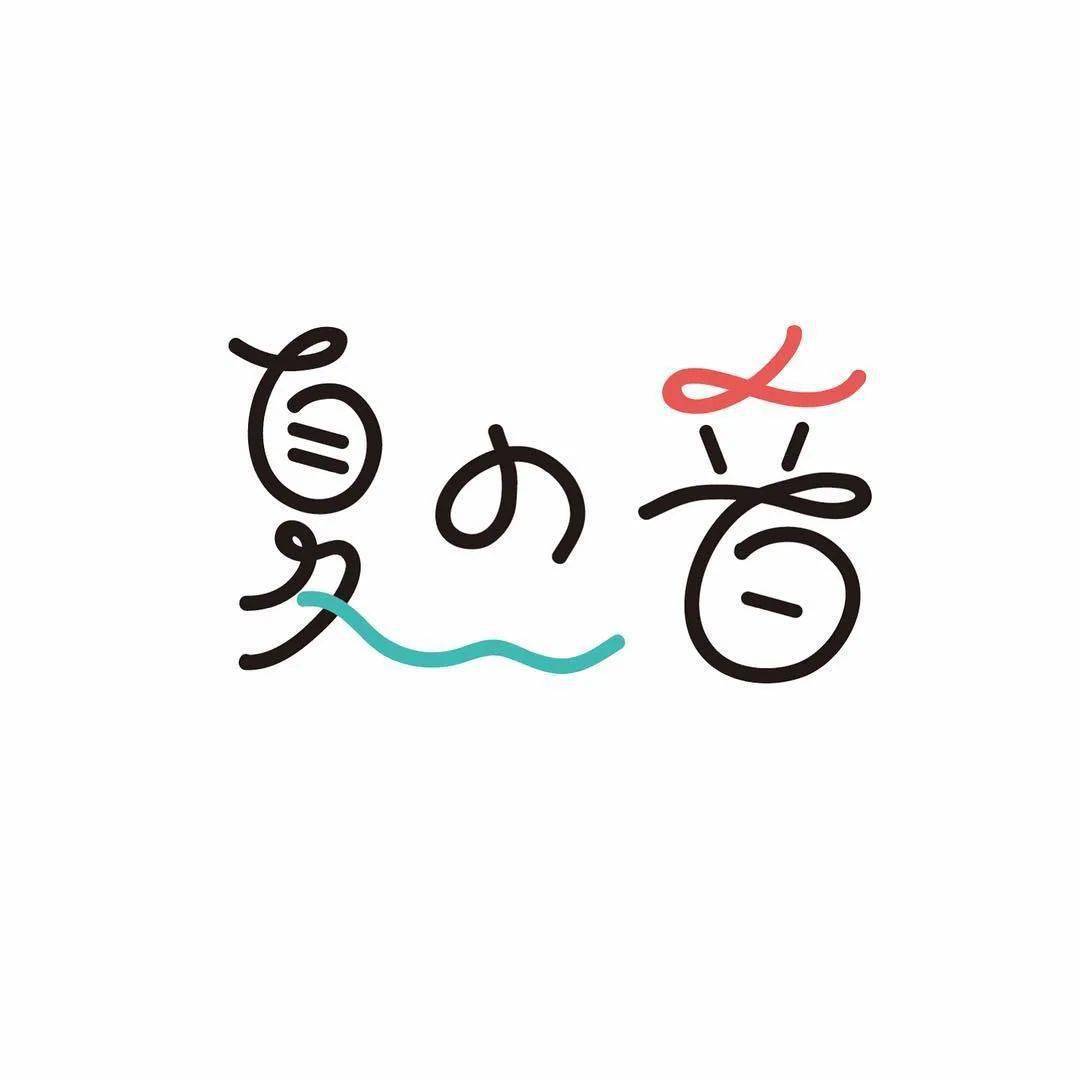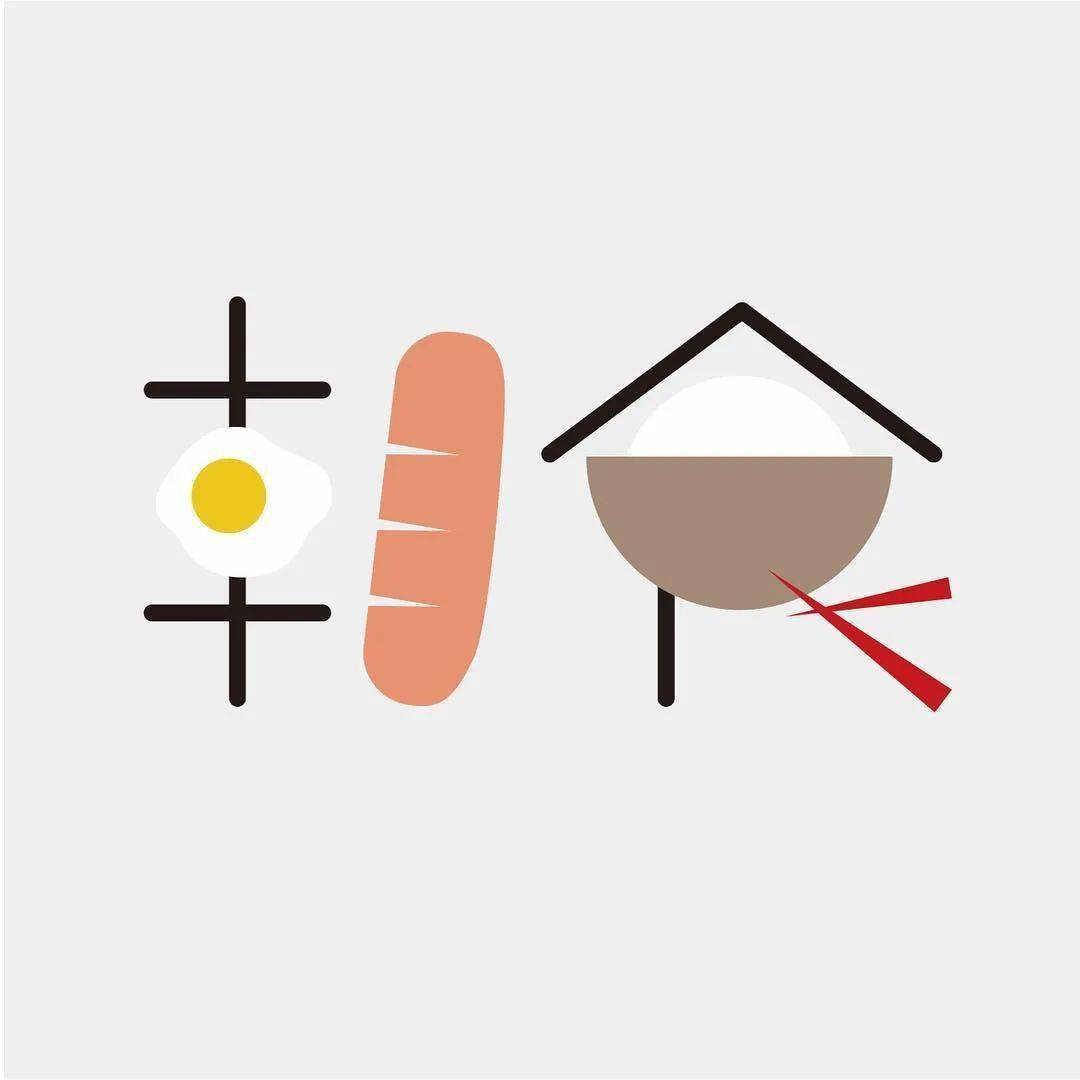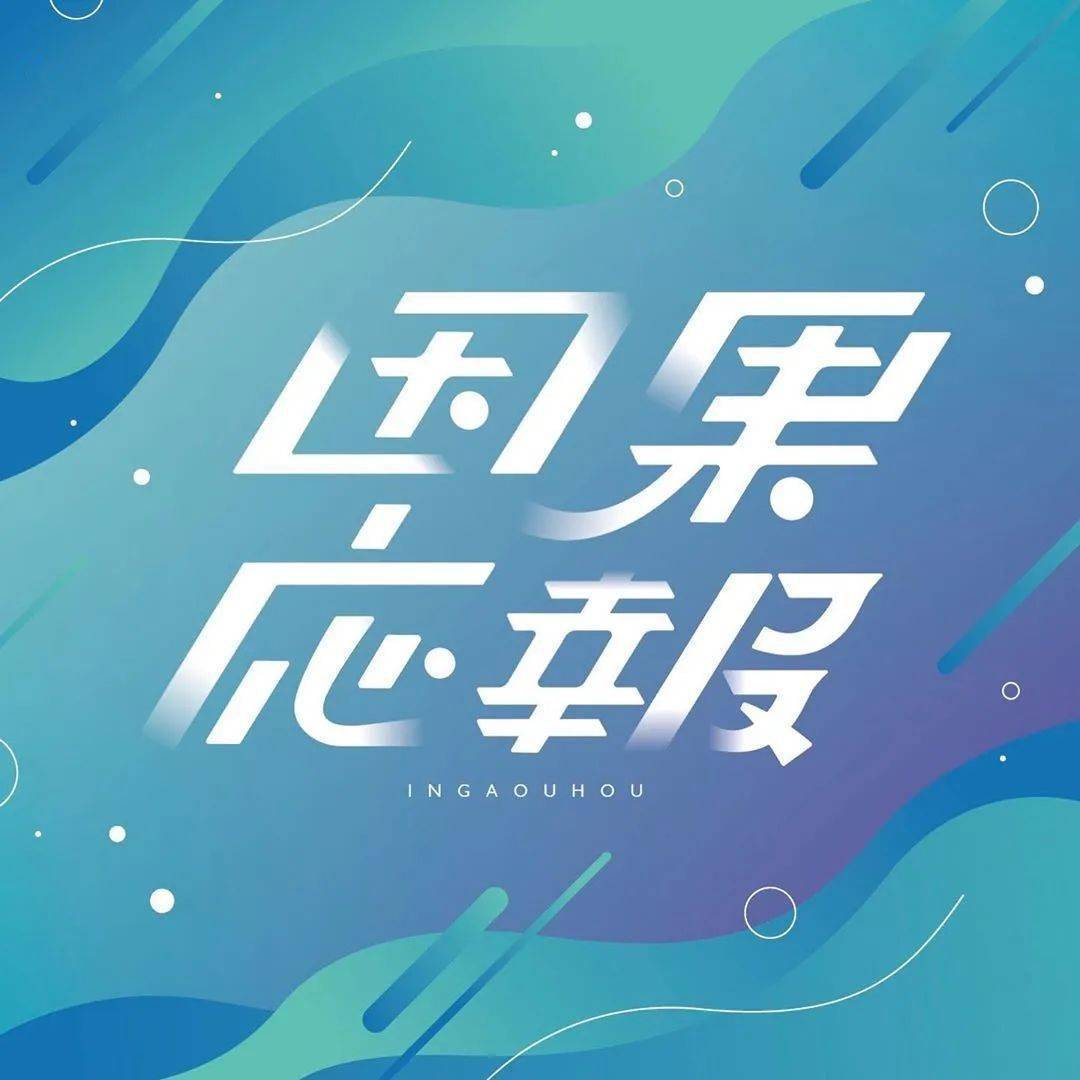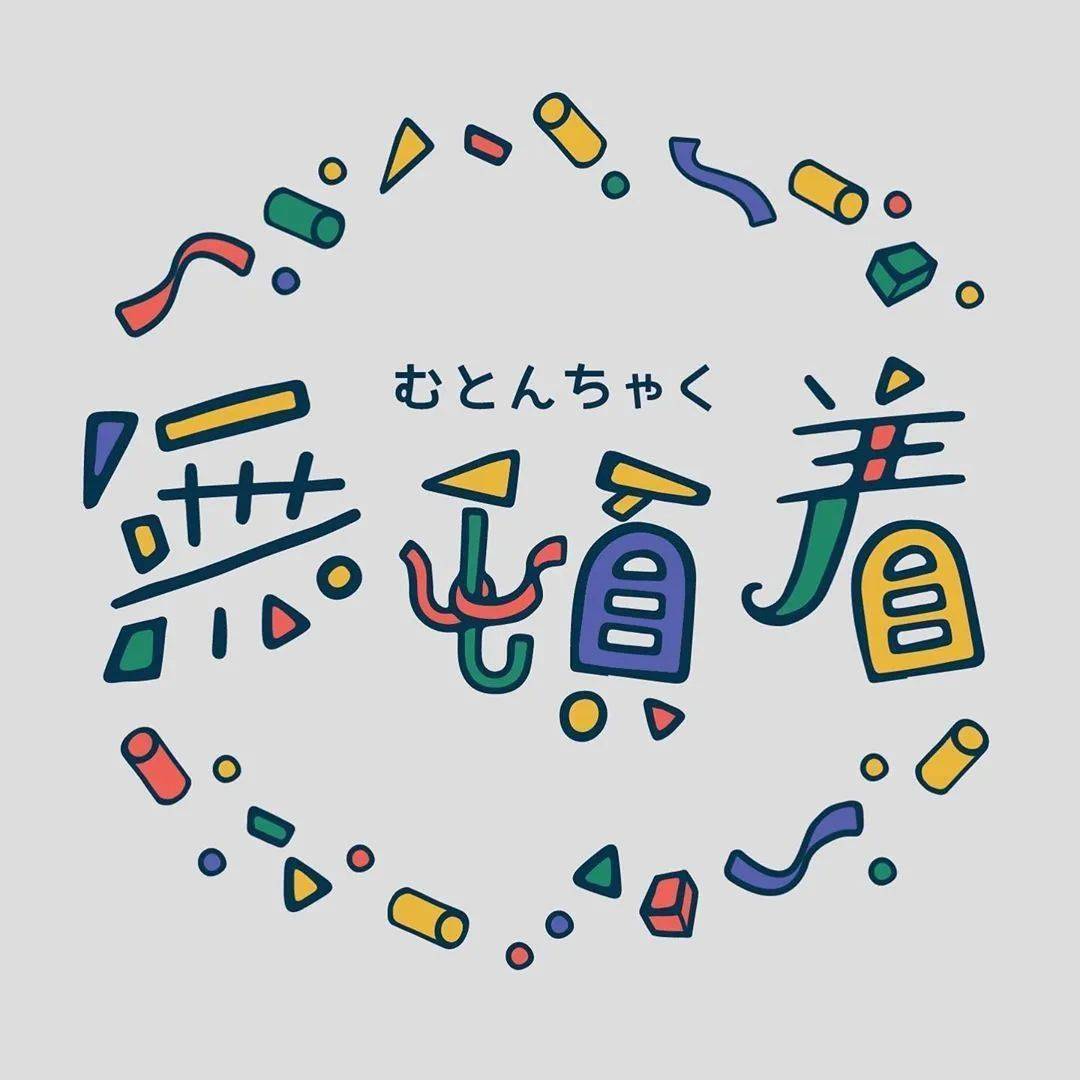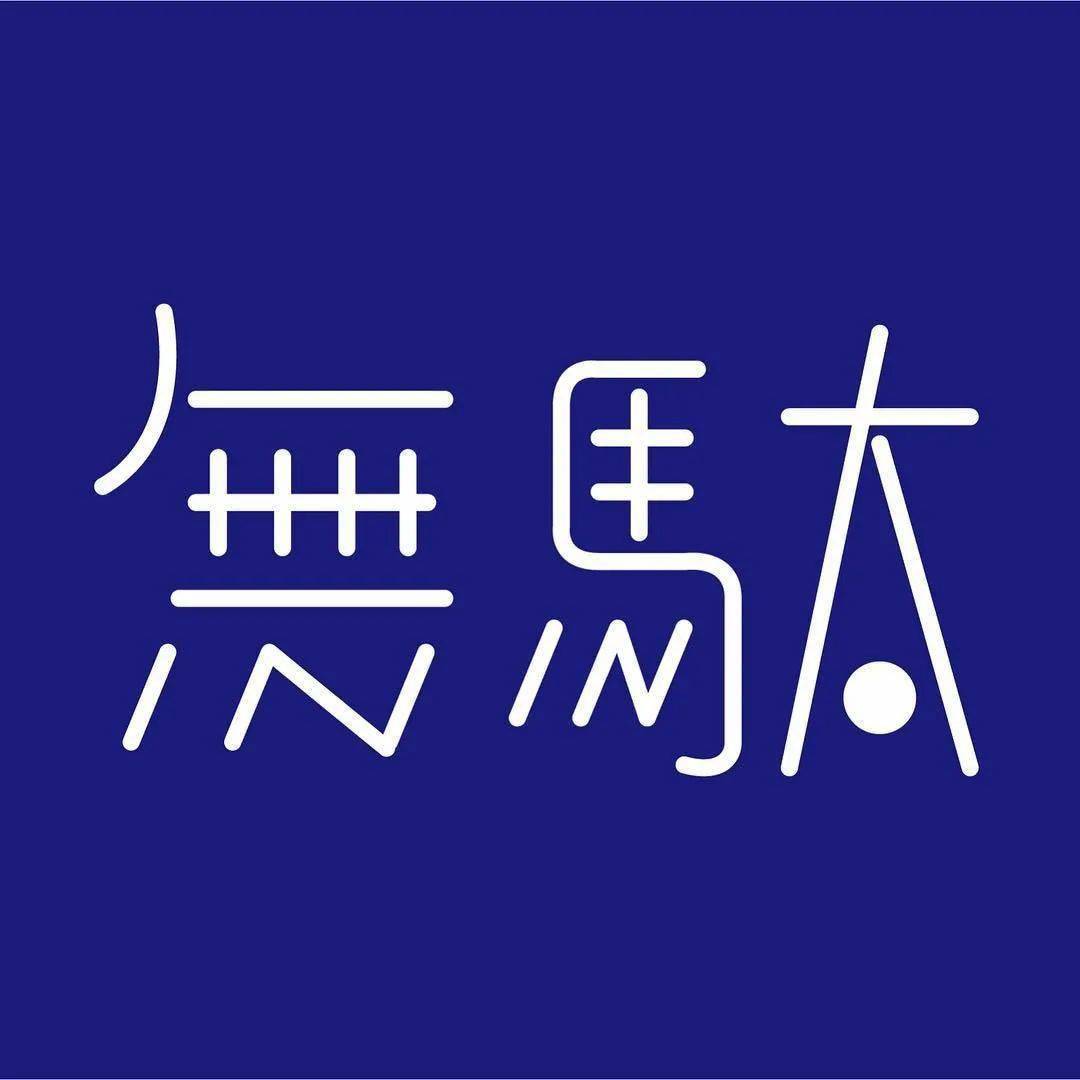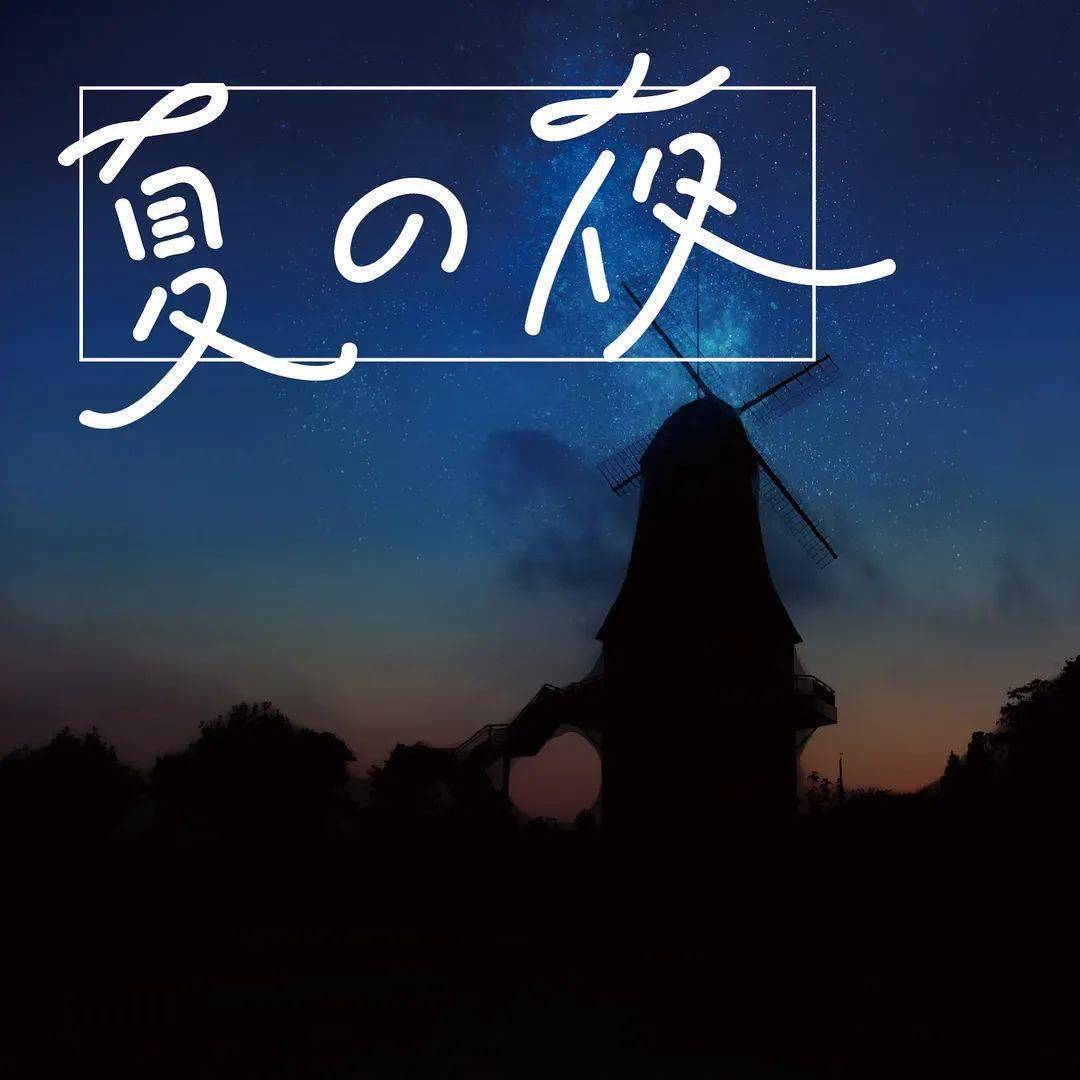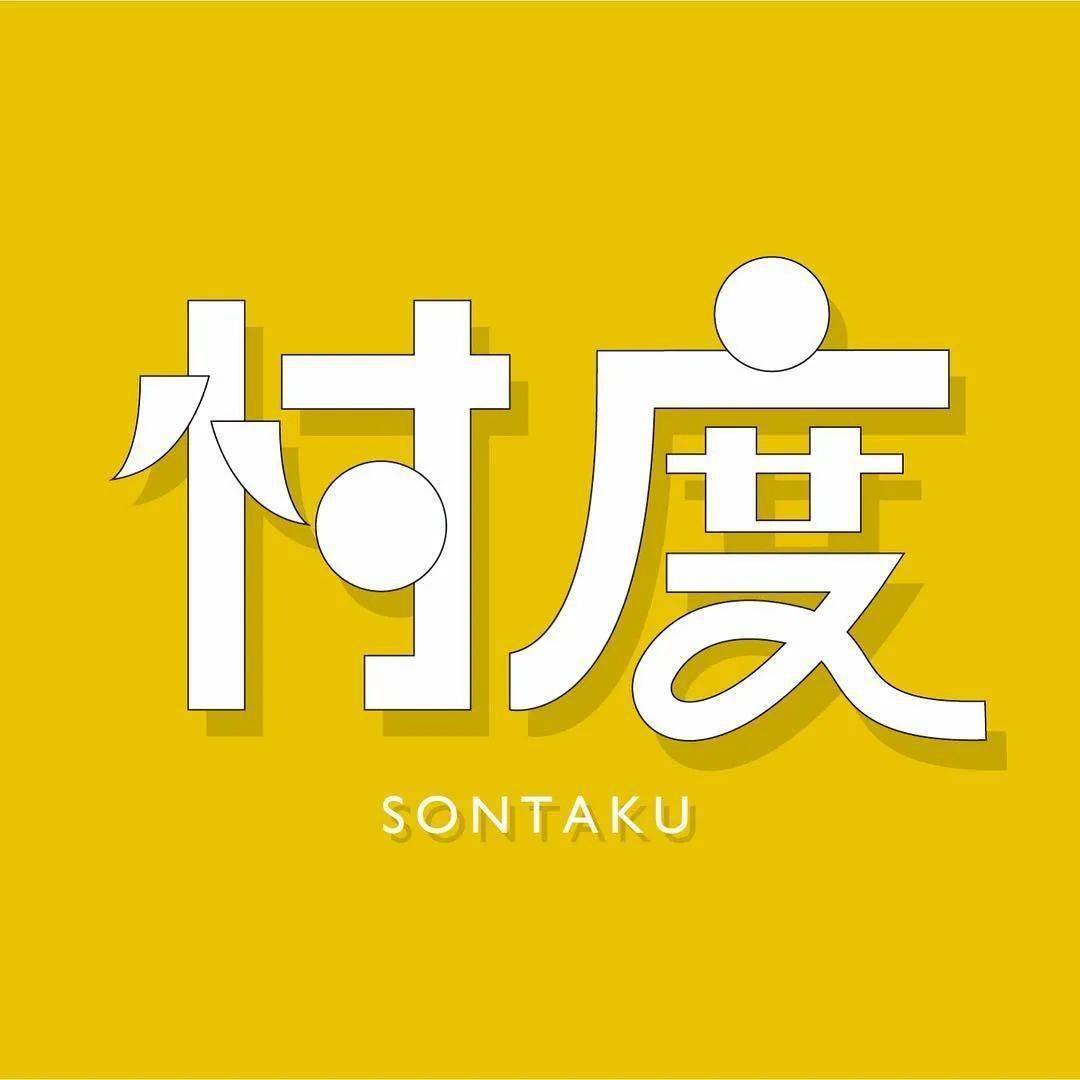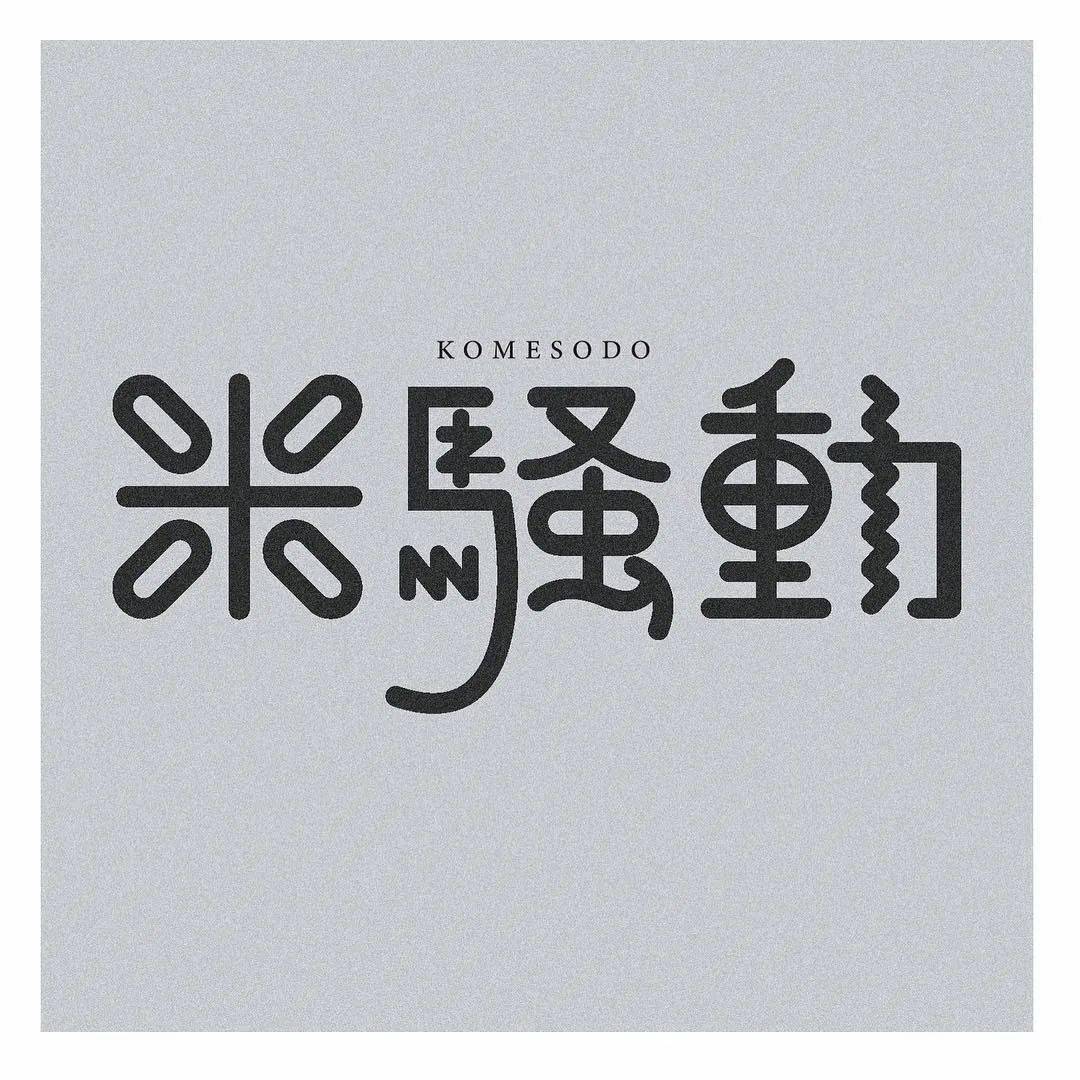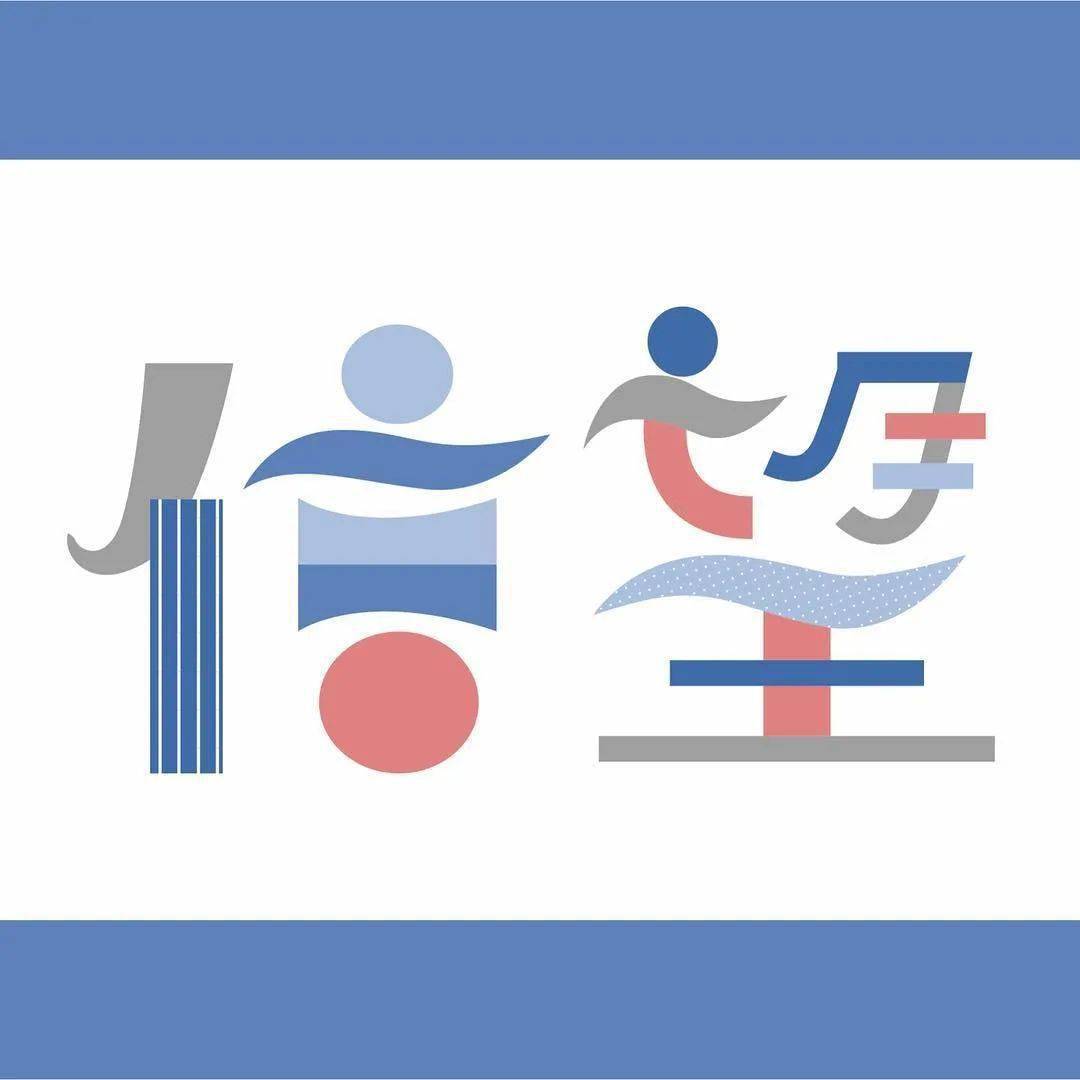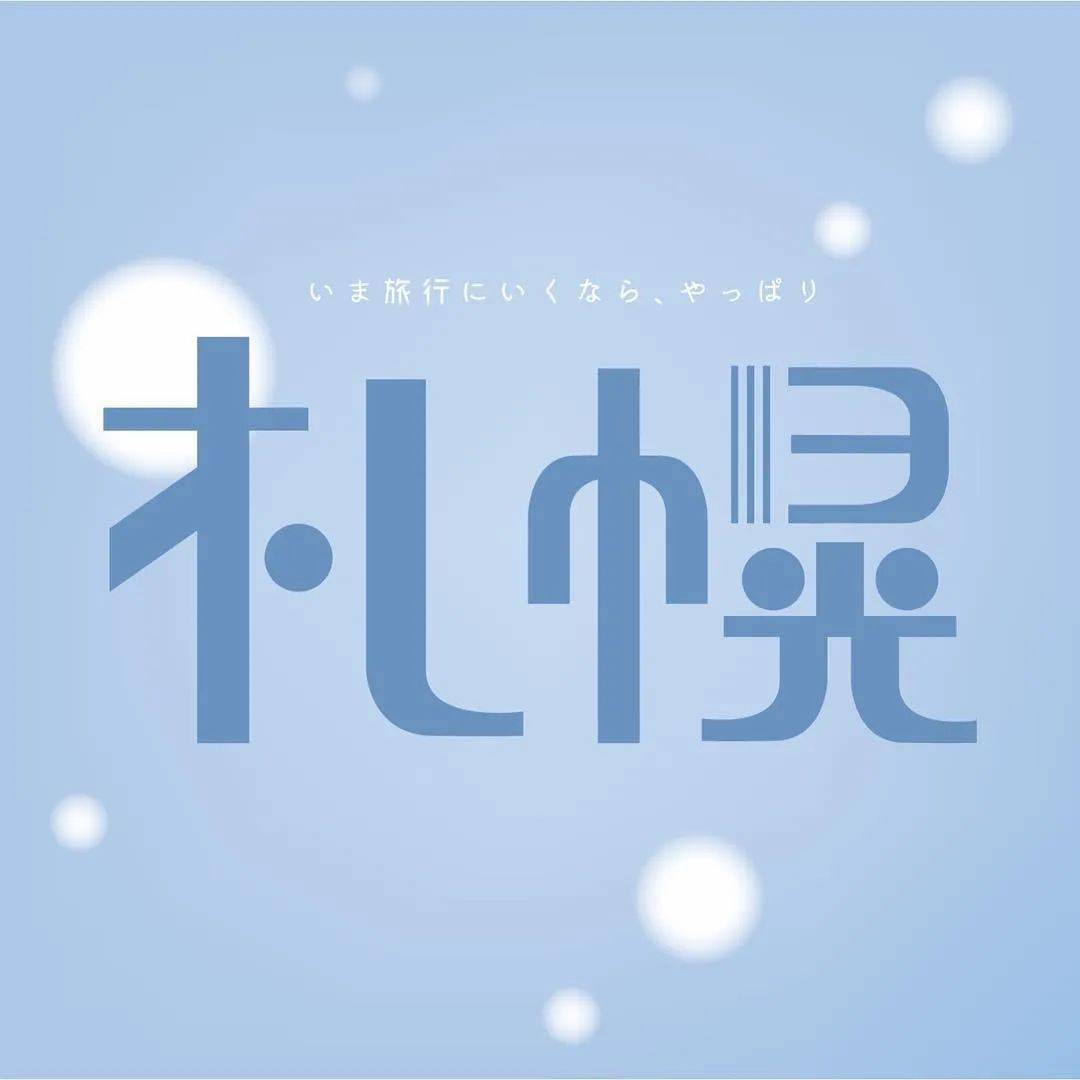
ayano.shibayama
分享设计师 ayano.shibayama 的64款字体设计作品
分享设计师 ayano.shibayama 的64款字体设计作品,各种设计风格及设计手法应有尽有,话不多说直接看作品吧, 希望大家能够从中收获一些字型方面的设计灵感。
字体设计有着丰富的蕴涵
千变万化的设计语言与视觉形式
几乎渗透到了平面设计的各个领域
注重文字表现形式上的形象、意象的创意方法
加入文字图形化的设计
从而拓展文字的表现空间
已成为现代字体设计艺术的一个新的领域